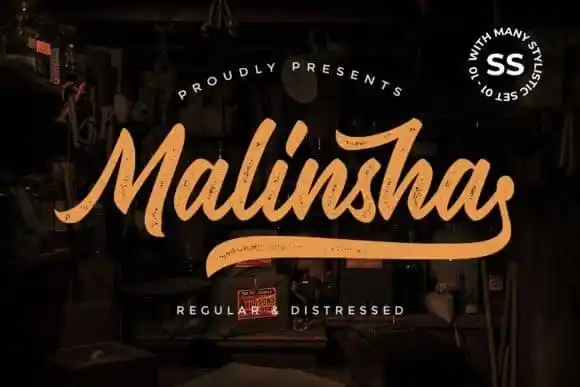
Malinsha Script Font – Download Grátis
A Malinsha Script Font é uma fonte tipográfica que se destaca pela sua beleza única, combinando tanto um estilo clássico quanto um toque vintage. Este projeto foi criado pelo Arterfak Project e agora pode ser compartilhado diretamente com você. Com seu aspecto único e fluente, essa fonte é perfeita para aplicação em cartões de agradecimento, frases curtas, cartões de boas-vindas, logotipos e muito mais. A Malinsha Script traz um toque nostálgico que certamente deixará seus projetos ainda mais elegantes. Se você está procurando por uma fonte que combine um ar clássico com um toque moderno e vintage, a Malinsha Script é definitivamente para você. Experimente incorporá-la em seu próximo projeto de design para agregar uma sensação única à sua composição.